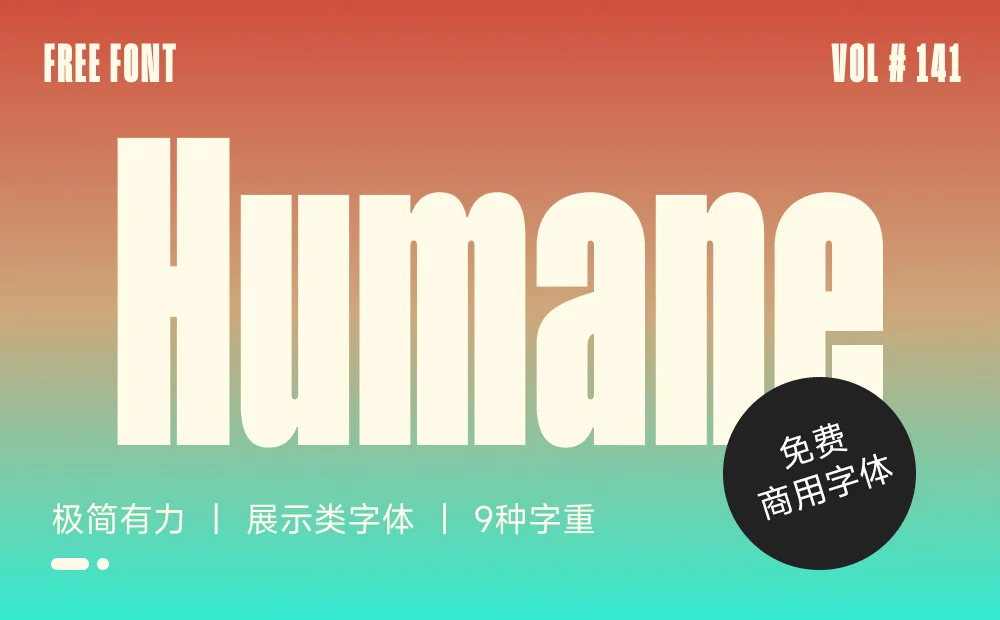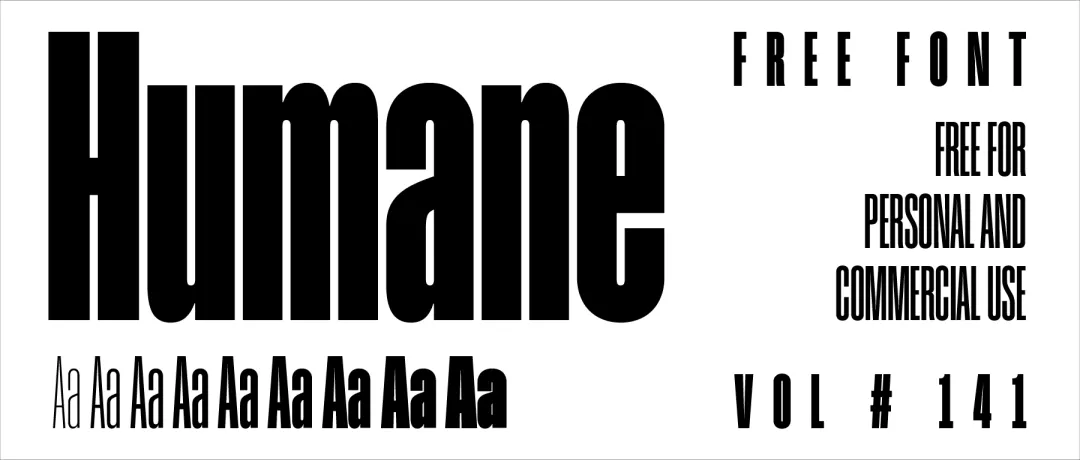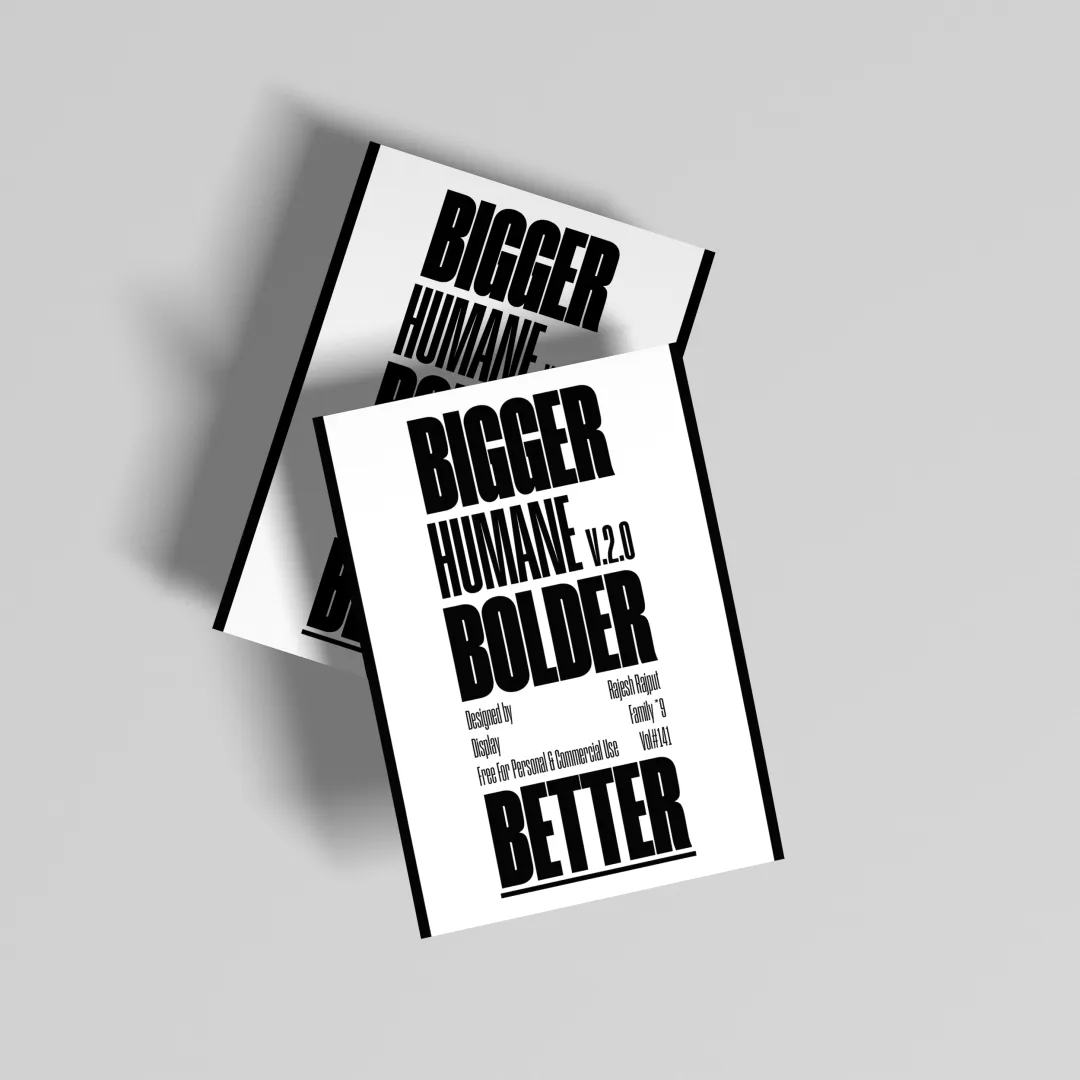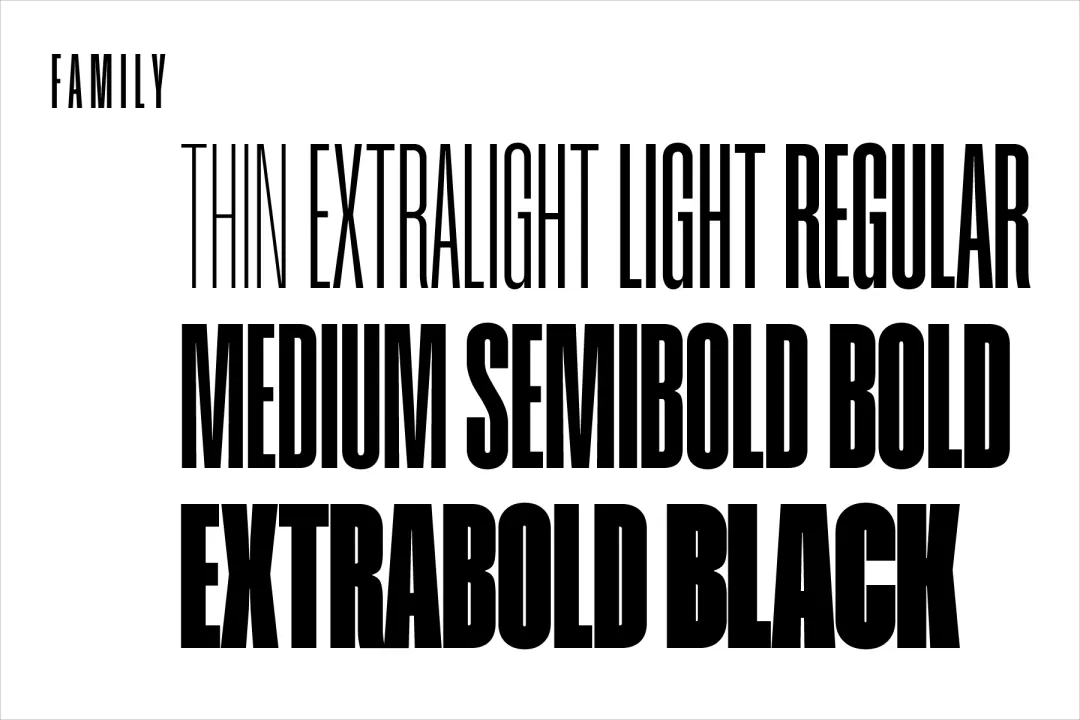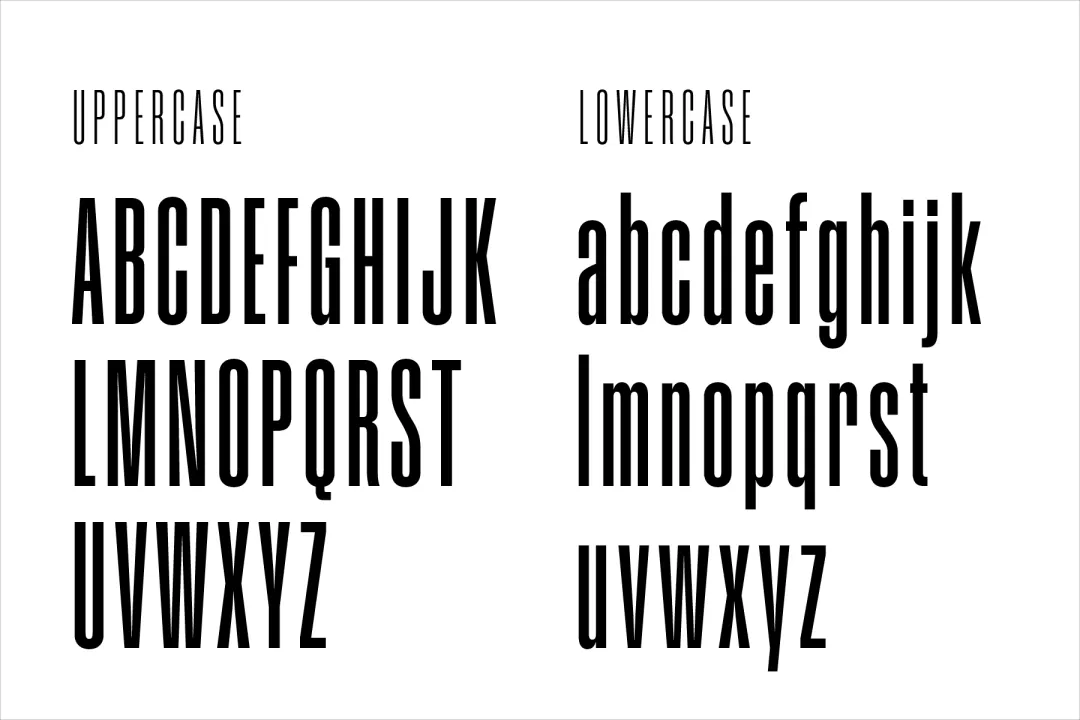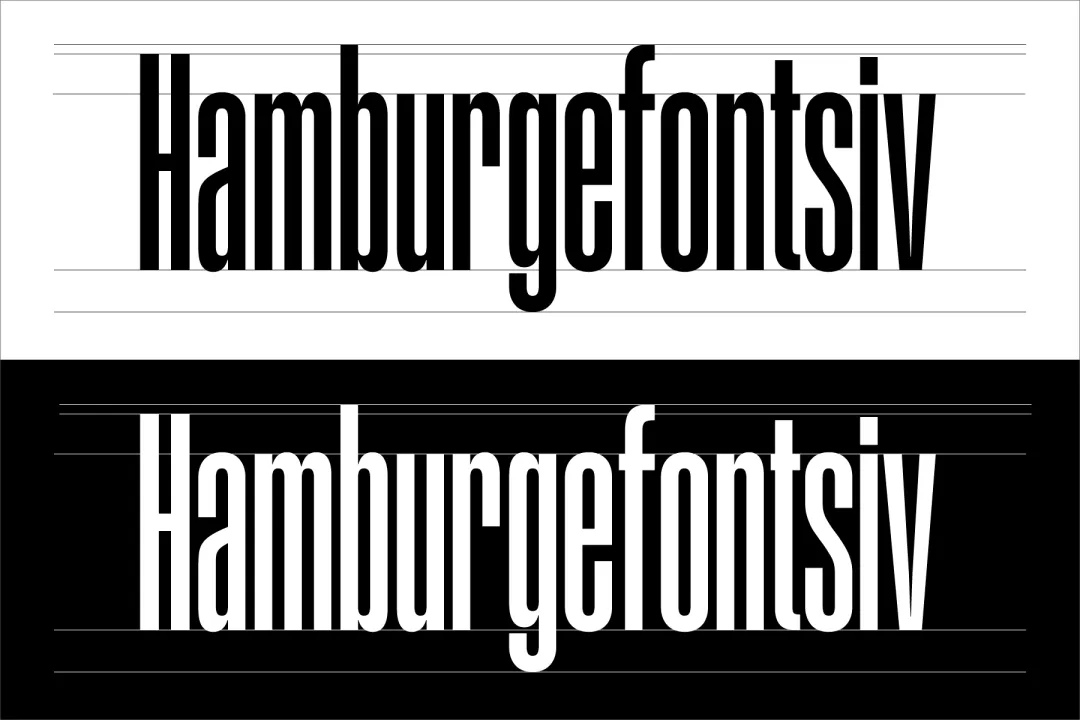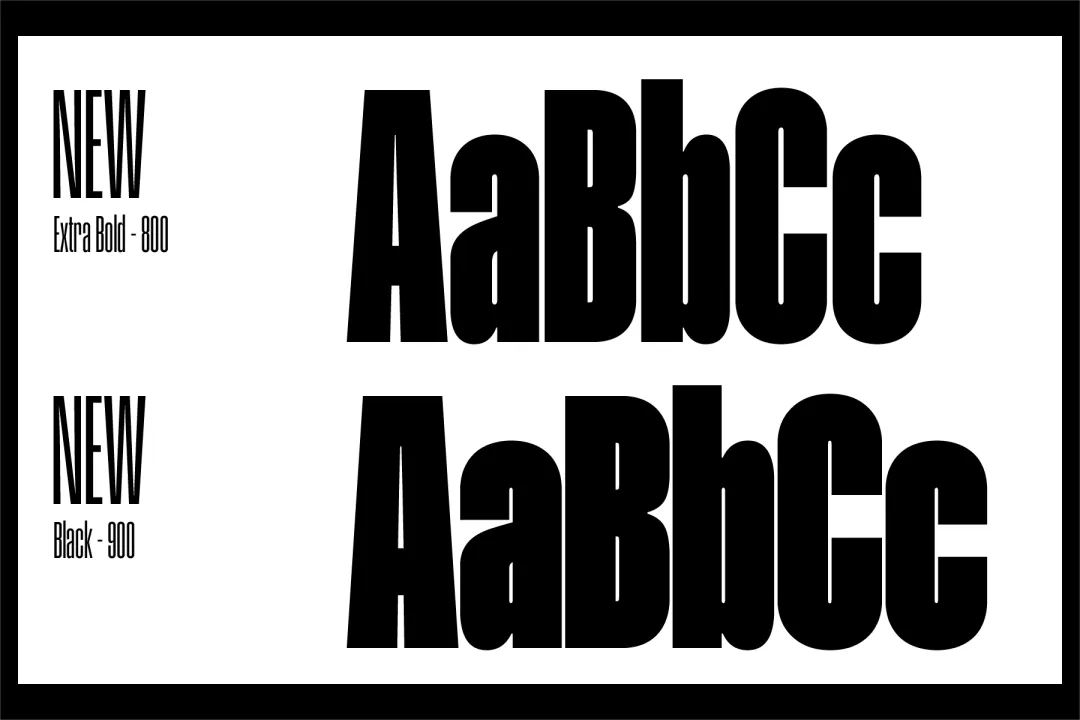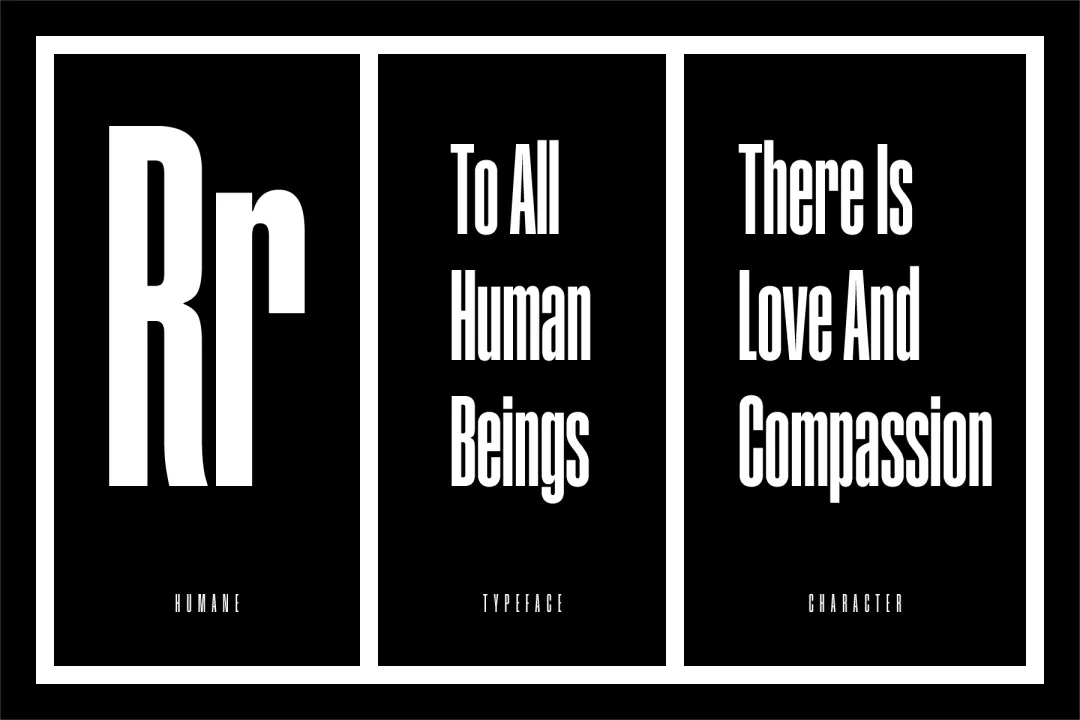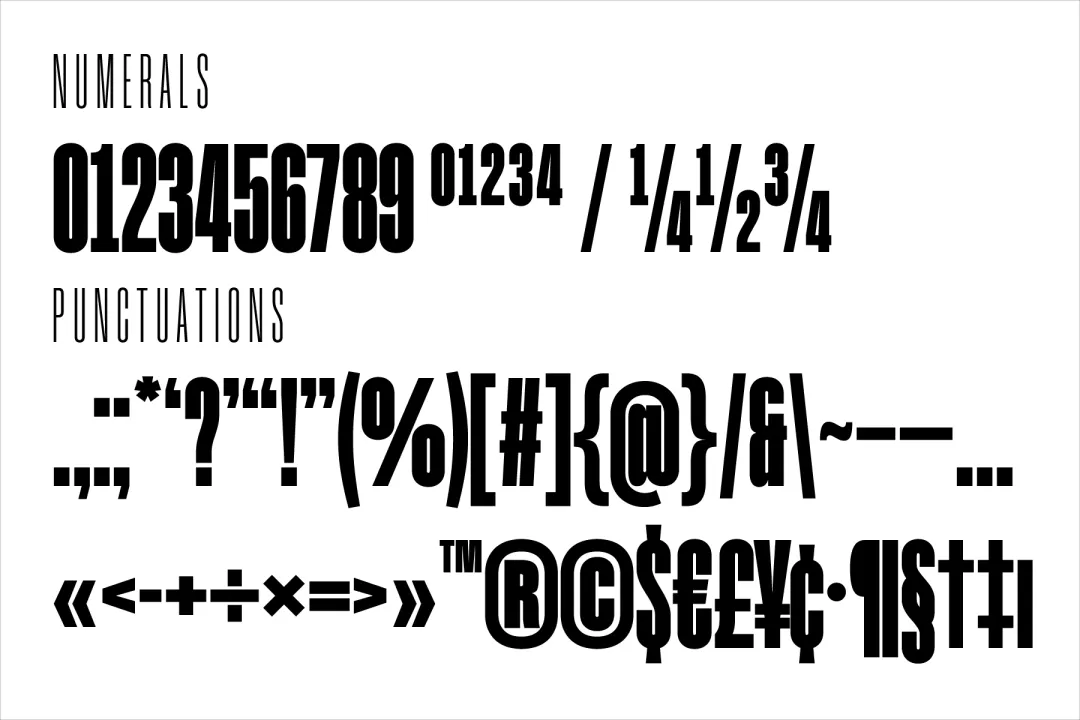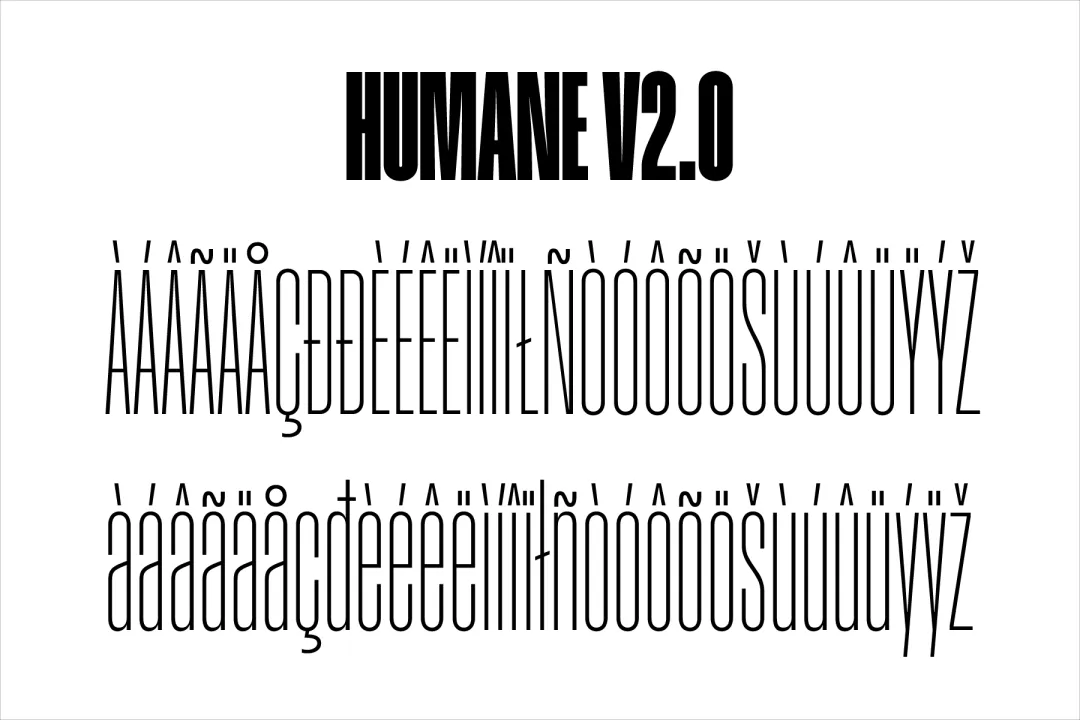
本期免费字体:Humane,来源于印度的 Rajesh Rajput ,是一款紧凑有力、极简而强大的展示类字体,家族具有9种不同粗细的字重,并且还是可变字体,能适应多种现代设计需求。
Humane 是一款超紧凑、现代感极强的无衬线字体,家族具有9种不同粗细的字重,并且还是可变字体;
Humane 在英文中的意思是 “人道的” 或 “仁慈的”,通常用来形容关心他人、体贴、具有同情心的品质,取名为 Humane,表达字体以人为本的特性;
Humane 是一款非常窄长的字体,每个字母都非常紧凑,但不影响可读性,突出了极简设计的美感;
之前在整理归纳的时候,发现字体已经推出了V2.0的版本,新增了更粗的2个字重,更有力量、更有冲击力;
Humane 每个字符经过精细调整,确保清晰和一致的视觉体验;
在V2.0中,作者优化调整了字符的间距、字距,以及较低的降部,提升了整体排版的平衡感;
同时也扩展了语言支持,包括改进的变音符号,适合更广泛的国际用户群体;
Humane 粗细对比非常的强烈,尤其在比较粗的字重中,笔画极其粗壮,适合传递力量感;
Humane 具有很强的现代感,字体的线条设计和极简的细节体现出符合当代审美的干净风格;
特别适合在大尺寸的广告和海报中应用,Humane 能展现极强的视觉吸引力;
用于标题文字或强调性内容,能在各种屏幕设备中保持高辨识度;
个人认为,Humane 还特别适合现代、科技类品牌的标志设计,以及时尚与创意产业,能够传递力量与个性;
以及视频字幕,在视频中用作大标题或短语文字,简洁、清晰、有力;
总结一下, Humane 是一款极简而强大的无衬线字体,拥有多样的粗细选项和出色的排版优化,能适应多种现代设计需求,尤其适合需要传递力量、紧凑感和现代美感的设计项目。